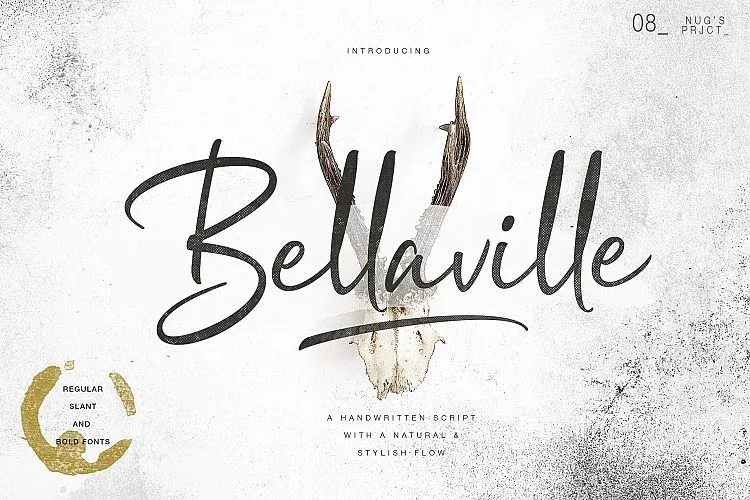
A Bellaville Script Font é uma nova opção para designers buscando uma fonte elegante e versátil. Inspirada no estilo handwritten com curvas naturais e formas únicas, esta fonte apresenta um estilo moderno e fresco, recheado de detalhes meticulosamente criados, que parecem ter sido escritos à mão por um artesão. Com uma linha base móvel e elementos decorativos incríveis, a Bellaville Script é perfeita para aplicações diversas como logotipos ou nomes de logotipos, marcações e até mesmo como texturas em imagens sem fundo. Ela traz um toque único de originalidade a qualquer projeto, tornando-a uma escolha excelente para designers que desejam dar um toque especial ao seu trabalho. Seja você criador de nomes de lojas, designer gráfico ou até mesmo editor de fotos, a Bellaville Script tem tudo o que precisa para dar o gás à sua próxima ideia visual.